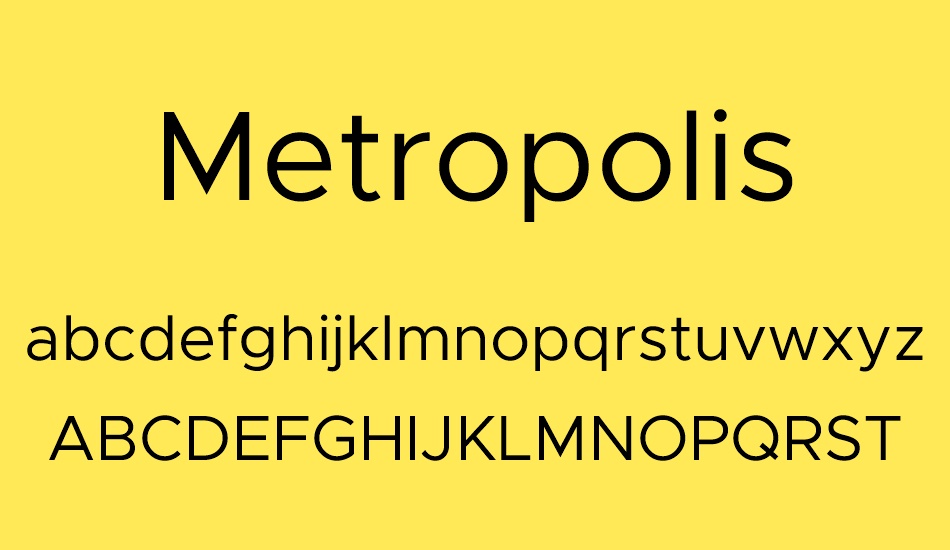
Metropolis font là bộ phông chữ thuộc dòng Geometric Sans-serif hiện đại được sáng tạo bởi Chris Simpson, lấy cảm hứng từ các tượng đài thiết kế hình học kinh điển như Futura hay Gotham nhưng được tối ưu hóa cho kỷ nguyên hiển thị số. Với các đường nét tròn trịa cân xứng, khung chữ thoáng đãng và tính ứng dụng linh hoạt, Metropolis font Việt hóa là chất liệu trực quan tuyệt vời để các kiến trúc sư, nhà thiết kế nâng tầm chuyên nghiệp cho các bản vẽ kỹ thuật CAD, hồ sơ năng lực dự án nhà lắp ghép hay hệ thống biển chỉ dẫn văn phòng container.
Cấu trúc hình học cân xứng và tính minh bạch thị giác của Metropolis font Việt hóa
Điểm cuốn hút của Metropolis font Việt hóa nằm ở cấu trúc hình thể chuẩn mực với các đường cong tròn hoàn hảo đan xen cùng những đường thẳng dứt khoát, loại bỏ những chi tiết rườm rà để hướng tới công năng hiển thị thuần túy. Chiều cao ký tự được căn chỉnh hợp lý giúp văn bản duy trì được khả năng đọc êm ái, rõ ràng ngay cả ở kích thước chữ nhỏ trên các bản vẽ chi tiết xây dựng.
Sự ổn định về mặt thị giác của dòng font này giúp truyền tải thông điệp về sự minh bạch, logic và tinh thần làm việc kỷ luật của đơn vị chủ trì dự án. Khi xuất hiện trên các bề mặt vật liệu kiến trúc hiện đại như tấm panel tôn phẳng sơn tĩnh điện, kính cường lực mờ hay nhôm định hình trong các công trình nhà lắp ghép thế hệ mới, Metropolis tạo nên sự tương thích thẩm mỹ cao, phù hợp với phong cách kiến trúc Minimalism hoặc High-tech.
| Phân loại phong cách | Geometric Sans-serif / Modern / Open Source |
| Số lượng biến thể | 18 kiểu (từ Thin đến Black kèm Italic) |
03 Ứng dụng phông chữ Metropolis vào thực tế dự án
Nhờ vẻ ngoài khoa học và sự rõ ràng trong cấu trúc nét, bộ phông chữ này mang lại giá trị thực tế lớn trong khâu quản lý và quảng bá các dự án xây dựng hiện đại:
- Ghi chú thông số trên bản vẽ AutoCAD: Độ sắc sảo của Metropolis giúp các dòng chú thích kích thước vật liệu panel, thông số kết cấu thép trở nên minh bạch, hỗ trợ đội ngũ giám sát thi công tại hiện trường tra cứu thông tin nhanh chóng và chuẩn xác.
- Hệ thống biển chỉ dẫn cho Văn phòng Container: Những nét chữ không chân hiện đại của Metropolis rất ăn ý khi gia công chữ nổi bằng inox hoặc mica dán kính, giúp không gian làm việc toát lên vẻ ngăn nắp và tinh tế.
- Bìa hồ sơ năng lực và Báo cáo dự toán công trình: Sử dụng phông chữ này cho các tiêu đề chương mục giúp tập hồ sơ trông như một ấn phẩm kiến trúc danh giá, tạo niềm tin lớn với các chủ đầu tư yêu chuộng phong cách làm việc chuyên nghiệp.
03 Lưu ý bố cục Metropolis font download duy trì tính mạch lạc
Để khai thác hiệu quả vẻ đẹp của dòng font Sans-serif hình học này mà không gây cảm giác đơn điệu cho trang in, người thiết kế nên lưu tâm một số kinh nghiệm sau:
- Kiểm soát khoảng cách dòng: Với cấu trúc chữ có chiều cao ký tự lớn, bạn nên thiết lập khoảng cách dòng thoáng đãng (khoảng 1.4 – 1.5 lần cỡ chữ) để các dòng văn bản không bị dính nét, giúp người đọc cảm thấy dễ chịu khi theo dõi các tài liệu dài.
- Bố trí khoảng thở tự nhiên: Bạn nên chừa khoảng trống xung quanh tiêu đề rộng rãi để các khối chữ hình học được hiển thị trọn vẹn, tránh việc để các chi tiết đồ họa phụ trợ chèn ép câu chữ.
- Đồng bộ phông chữ trên mọi nền tảng: Hãy duy trì sử dụng Metropolis từ bản vẽ kỹ thuật CAD đến slide trình chiếu báo cáo dự án để tạo nên sự nhất quán trong hình ảnh thương hiệu của đơn vị thi công.